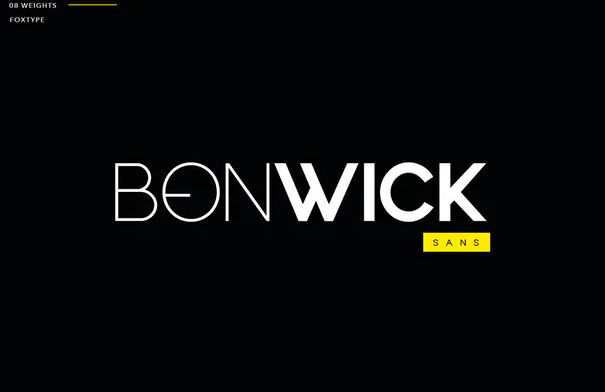
Bonwick Display
- уникальный современный элегантный шрифт с веб-шрифтами.
Это очень универсальный шрифт, который отлично работает в больших и малых размерах. Шрифт Bonwick идеально подходит для брендинга, логотипов, заголовков, подписей или просто как стильный текст, наложенный на любое фоновое изображение. Сильные заглавные буквы и гладкий, открытый строчный регистр эффективны в различных областях применения. Шрифт демонстрирует чистоту, минимализм, теплоту, причудливость, но все же призван быть универсальным и легко читаемым.